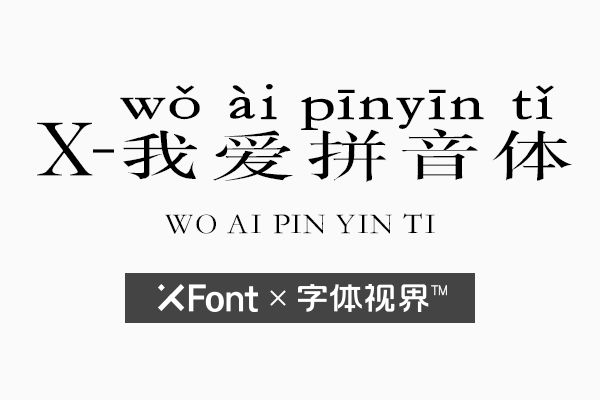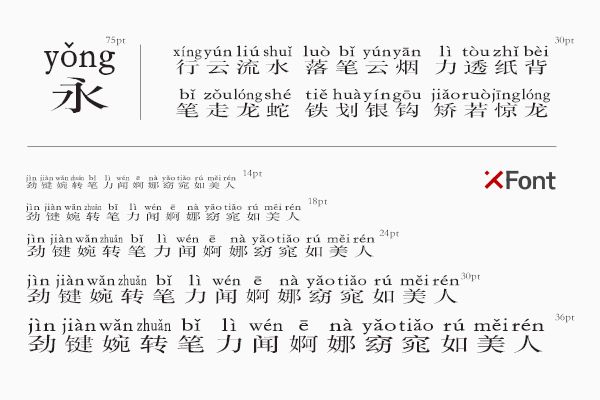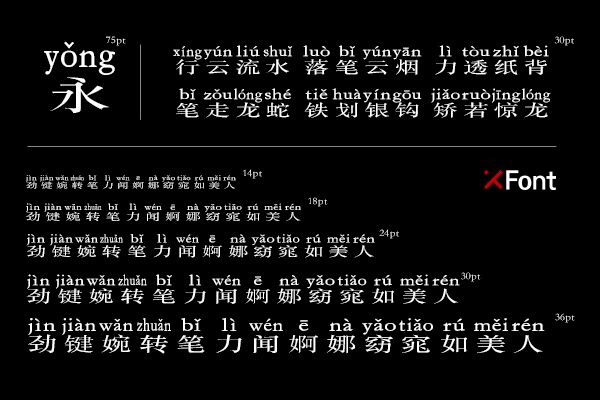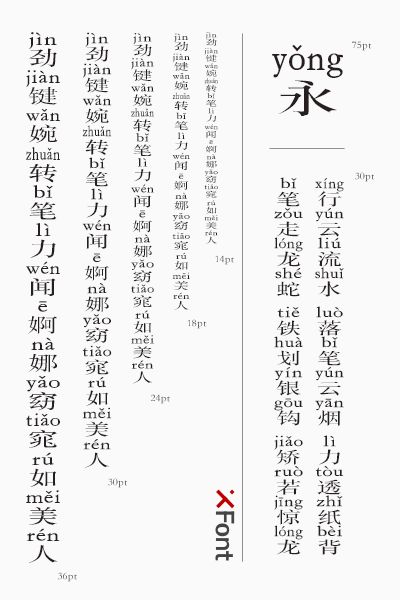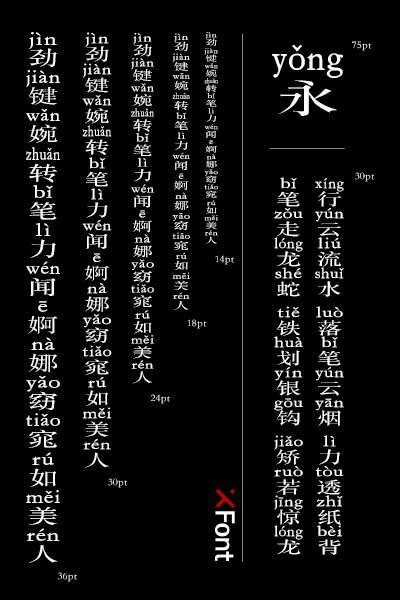
XFont-我爱拼音体字体,字体大全里的“出淤泥而不染”。
在宋代时,便有了周敦颐先生的《爱莲说》,其中有一句印象深刻的句子便是:“予独爱莲之出淤泥而不染,濯清涟而不妖。”,表达了对自己的评论,这也是对他清廉的生活作风一种描绘。犹如这款代表正直、清廉且不与现代流行字体所趋同的风格。
今天要介绍的这款字体就是XFont-我爱拼音体,这款字体虽然看上去很普通,但是却是少有的拼音体并且不管在拼音还是文字上,都显的非常正直和标准。这款拼音体拥有标准的文字并辅以标准拼音,犹如两位正直的检察官一样,相互检查、互相监督,在字里行间无不透露着那铿锵有力的正直风气,就像引领着我们去学习这优秀的生活作风。
这标准的拼音体能提醒着我们学习母语的重要性,还可以帮助我们更好阅读和运用,在整体拼音和字体有机地整合在一起,让观赏者映入眼帘,感受到莲花出淤泥而不染那意境优美的情景图。
这款字体结构是以标准文字和标准拼音构成的,和XFont-拼音aoe字体相似,并没有任何的艺术效果,但只正是因为如此,才能使其更好的变得富有正直和清廉的笔势,让观赏者感受到标准字体的美,简单且标准的字库,表现出使用者出淤泥而不染的生活风气。
这款字体的设计师,设计出这款标准且代表正直的拼音体,适用于正规场合,使用这款XFont-我爱拼音体字体能贴切的表现出正直清廉的风格,从整体上使观赏者感受到那出淤泥而不染的字体风格。